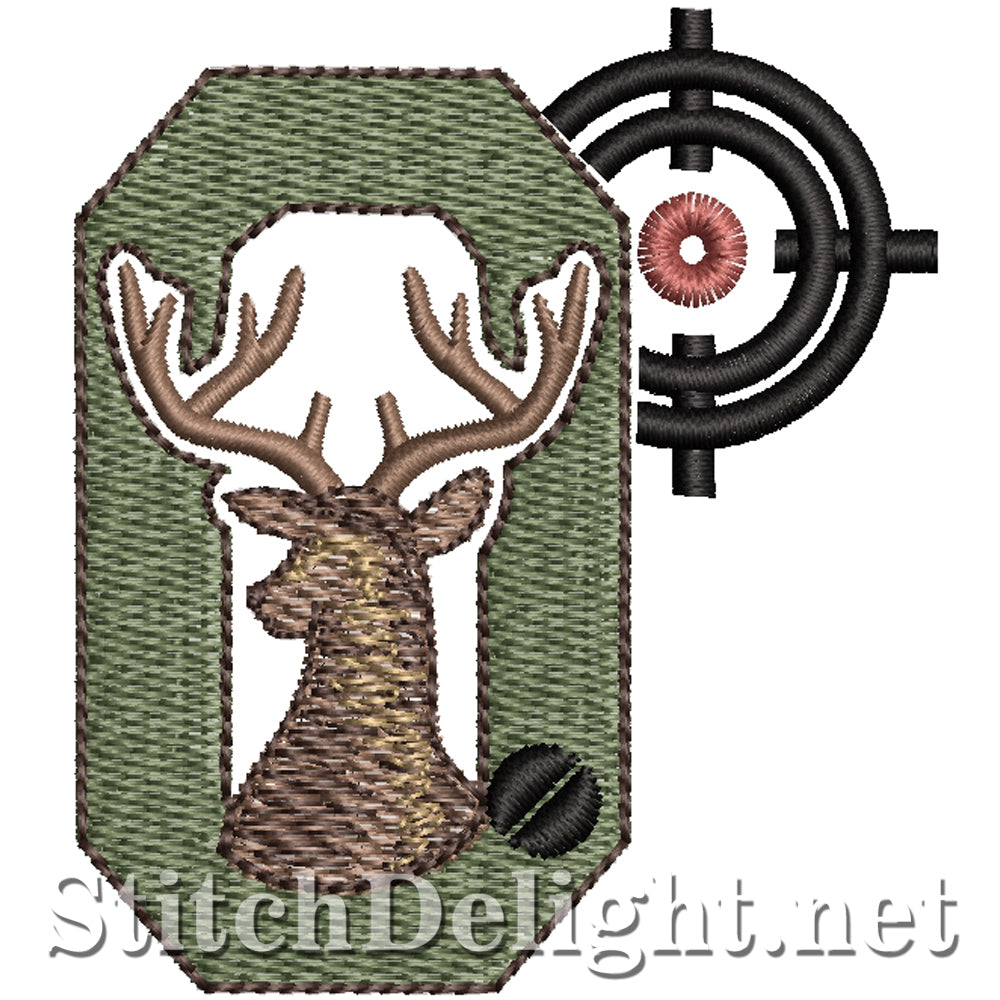
Police SDS1752 Hunters O
C'est une police indispensable pour les passionnés de chasse. Avec une hauteur moyenne de 3" cette lettre simple est parfaite pour coudre sur des sacs de rangement de fusil.